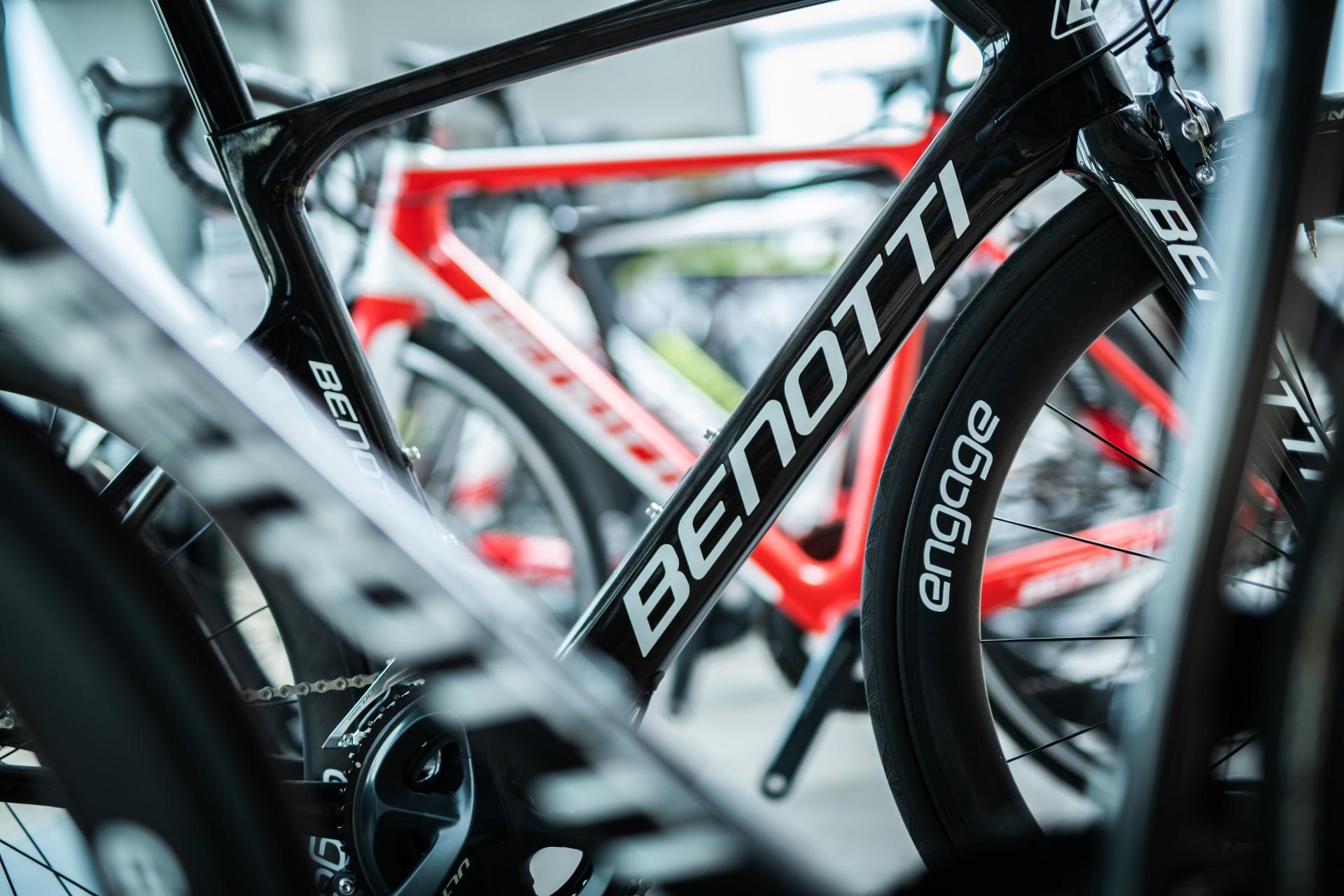
Suche Schriftart aus einem Foto (BENOTTI Fahrrad)
wegen Umlackierung suche ich folgende Schriftart auf dem Foto  "BENOTTI"
Gunship von Iconian Fonts wäre einen genaueren Blick wert.
Aus dieser Ecke kommt die Schrift und es gibt auch einige sehr ähnliche Schriften mit ggf. passenderer Strichdicke. Viel Glück bei der weiteren Suche.
Nachtrag: Die Schreibweise in Kleinbuchstaben ergibt das erwünschte Schriftbild.